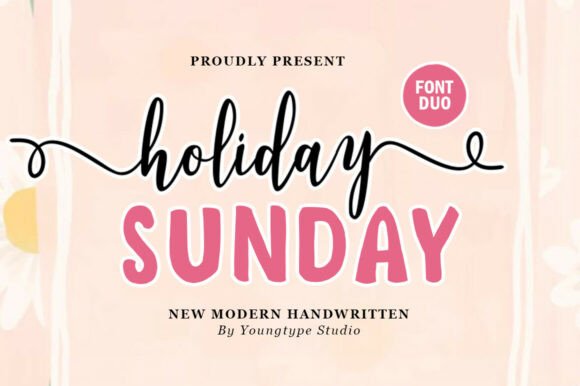
Holiday Sunday Duo
Holiday Sunday Duoのような高品質の素材をお探しの場合、このプレミアムパッケージはクリエイティブなプロジェクトに素晴らしい選択です。
精密に作られたHoliday Sunday Duoは、クリーンなベクター、滑らかなタイポグラフィ、そして安心のための商用ライセンスを提供します。
POD(オンデマンド印刷)製品、結婚式の招待状、またはソーシャルメディアのグラフィックを作成している場合でも、Holiday Sunday Duoは理想的です。